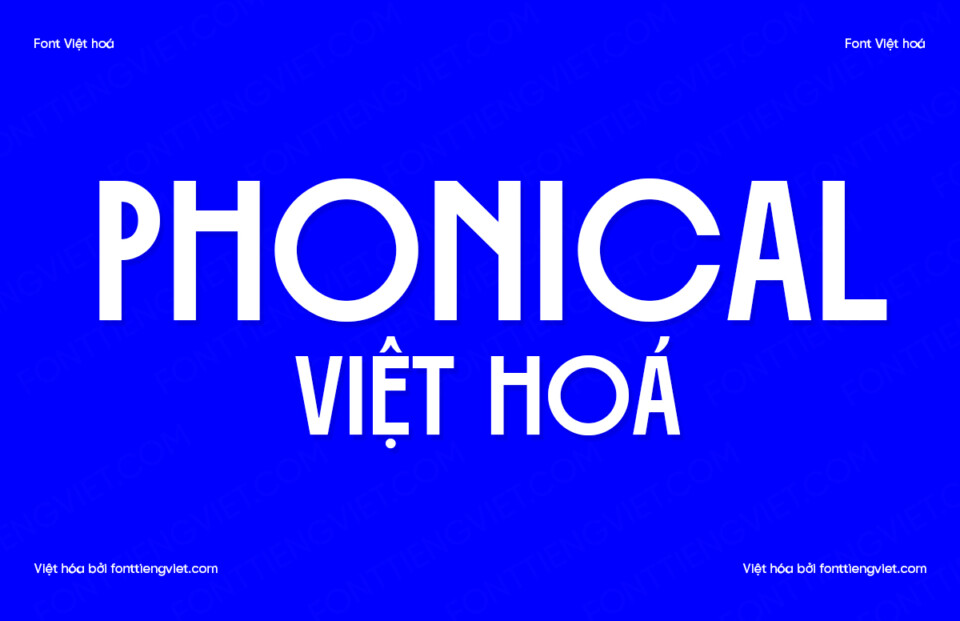
Tìm Kiếm Font Việt hóa 1FTV VIP Phonical Độc Đáo Cho Thiết Kế Trường HọcGiới thiệu về Font Việt hóa 1FTV VIP Phonical trong giáo dụcTrong môi trường giáo dục hiện đại, việc truyền tải thông tin một cách trực quan và thu hút là vô cùng quan trọng. Một Font Miễn Phí chất lượng không chỉ giúp bài giảng sinh động mà còn kích thích tư duy sáng tạo của học sinh. Hiện nay, bộ Font Việt hóa 1FTV VIP Phonical đang trở thành lựa chọn hàng đầu của nhiều giáo viên và các bạn học sinh nhờ phong cách thiết kế hiện đại, rõ ràng và vô cùng thân thiện.Ưu điểm nổi bật của Font Việt hóa 1FTV VIP PhonicalThiết kế tối ưu cho học tậpBộ font này sở hữu các đường nét thanh thoát, dễ đọc, giúp giảm mỏi mắt khi theo dõi bài giảng dài trên máy tính hoặc bảng tương tác. Tính năng Việt hóa hoàn chỉnh giúp các thầy cô yên tâm soạn thảo giáo án điện tử mà không lo lỗi dấu tiếng Việt.Ứng dụng đa dạng trong nhà trườngCác bạn học sinh có thể dùng font chữ này để làm báo tường, thiết kế slide thuyết trình bài tập nhóm, hay trang trí thời khóa biểu. Sự linh hoạt của phông chữ giúp mọi ý tưởng sáng tạo học đường trở nên chuyên nghiệp và bắt mắt hơn bao giờ hết.Lưu ý khi sử dụng Font Việt hóa 1FTV VIP Phonical trên websiteCách phối màu sắc phù hợpKhi thiết kế slide hoặc tài liệu học tập, bạn nên kết hợp bộ font này với các tông màu nền sáng như trắng, xanh nhạt hoặc kem để tạo độ tương phản tốt nhất cho văn bản.Kích thước hiển thị tiêu chuẩnĐối với nội dung bài học, kích cỡ từ 14 đến 16pt là lý tưởng nhất để các em học sinh ở cuối lớp vẫn có thể quan sát rõ ràng.Kết luận và hướng dẫn tải font chữ học đườngViệc lựa chọn công cụ thiết kế phù hợp sẽ nâng cao hiệu quả giảng dạy và học tập một cách rõ rệt. Hãy truy cập ngay kho dữ liệu để tải Font Miễn Phí, Font Việt Hóa, Font Việt hóa 1FTV VIP Phonical và bắt đầu sáng tạo những bài giảng tuyệt vời cho nhà trường ngay hôm nay.
Font Việt hóa 1FTV VIP Phonical